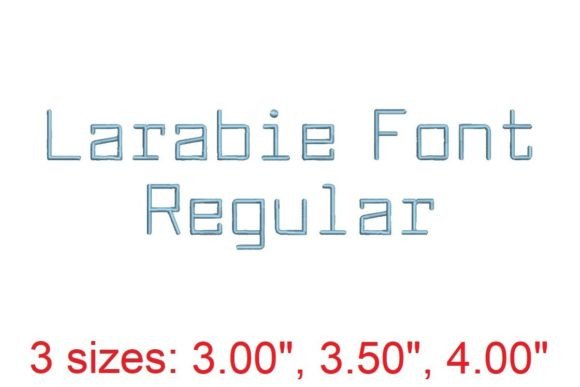
Larabie Font LT Embroidery Font
Mencari elemen desain yang tepat bisa jadi sulit, namun Larabie Font LT Embroidery Font menawarkan koleksi luar biasa yang akan langsung meningkatkan kualitas karya Anda.
Baik Anda membuat produk POD (Print on Demand), undangan pernikahan, atau grafis media sosial, Larabie Font LT Embroidery Font adalah pilihan yang sangat ideal.